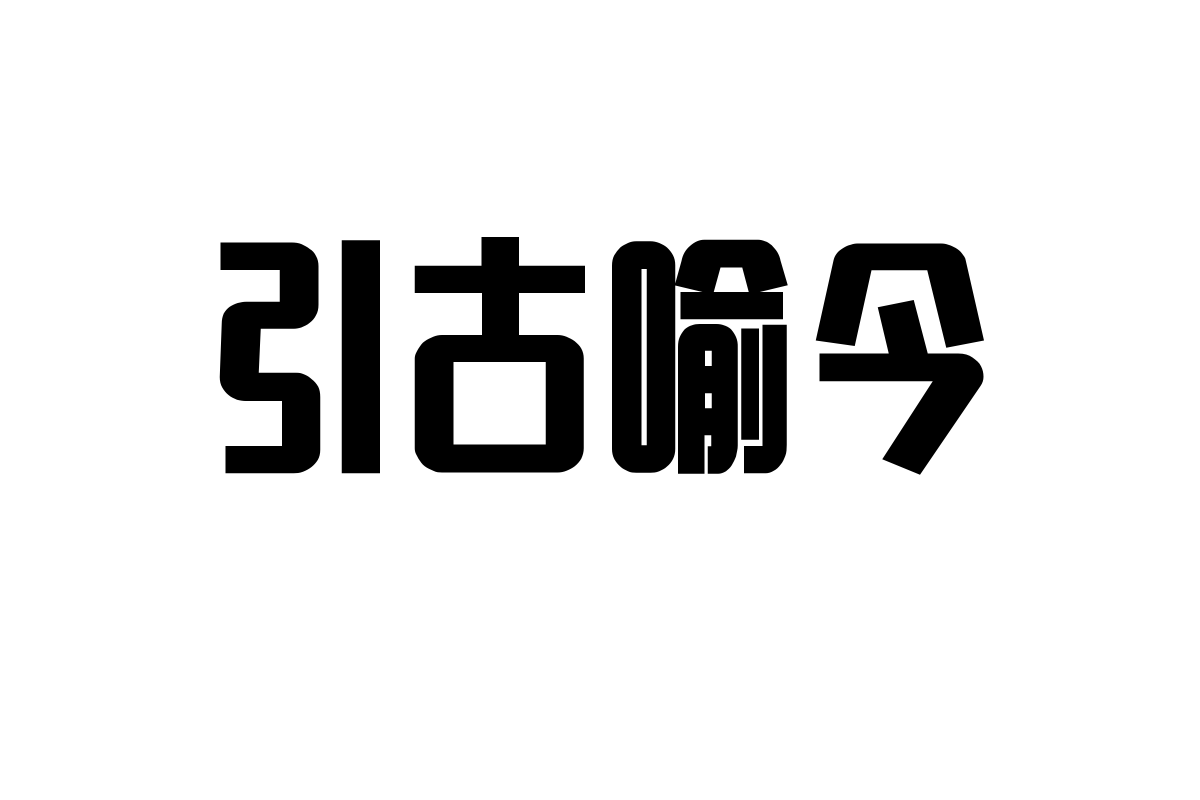
汉仪晓波画报黑是一款专为中文书写设计的字体,具有独特的艺术风格和现代感。这款字体采用了简洁的线条和形状,给人一种干净、清爽的感觉。它适合用于各种文本、标题和广告设计,能够很好地表达出文字的美感和个性。
在细节上,汉仪晓波画报黑采用了一些特殊的笔画和结构,使得整体看起来更加独特和有趣。例如,它的横线和竖线都采用了不同的粗细和角度,形成了独特的视觉效果。此外,它还在一些笔画上进行了加粗处理,使得整个字体更加醒目和引人注目。
总的来说,汉仪晓波画报黑是一款非常实用的中文字体,适合用于各种需要展现文字美感和个性的设计项目。无论是用于印刷还是电子显示,都能够展现出其独特的魅力和效果。